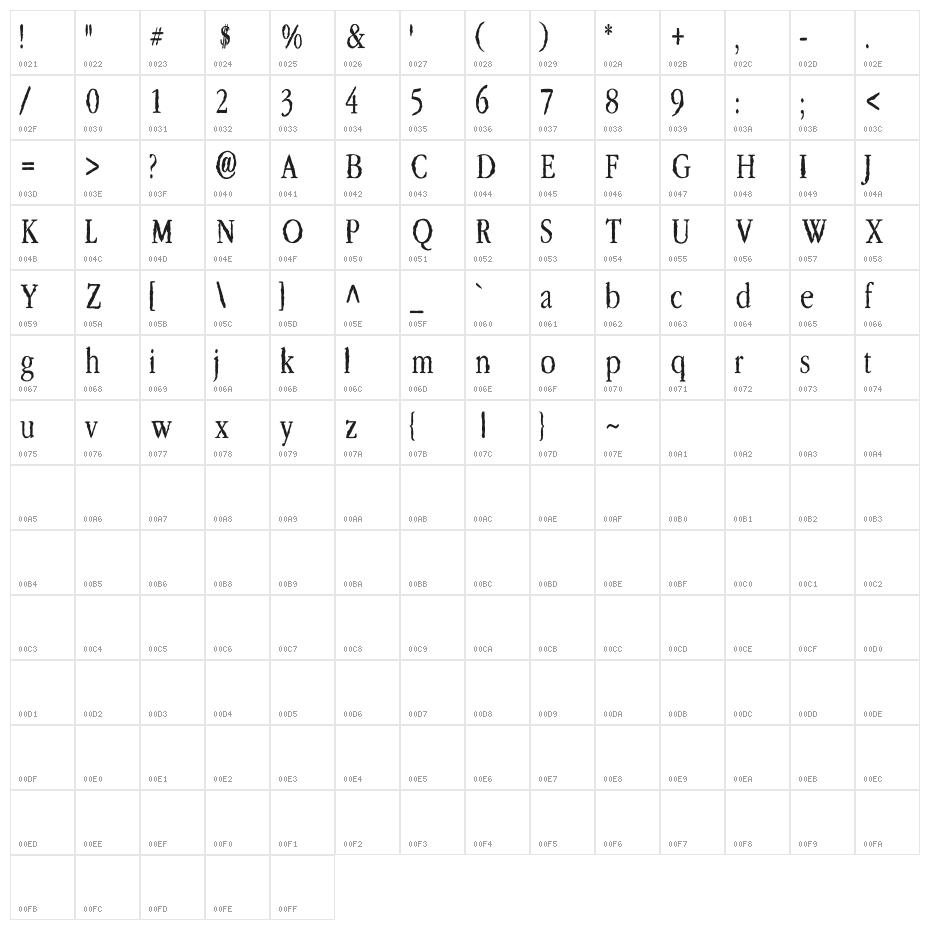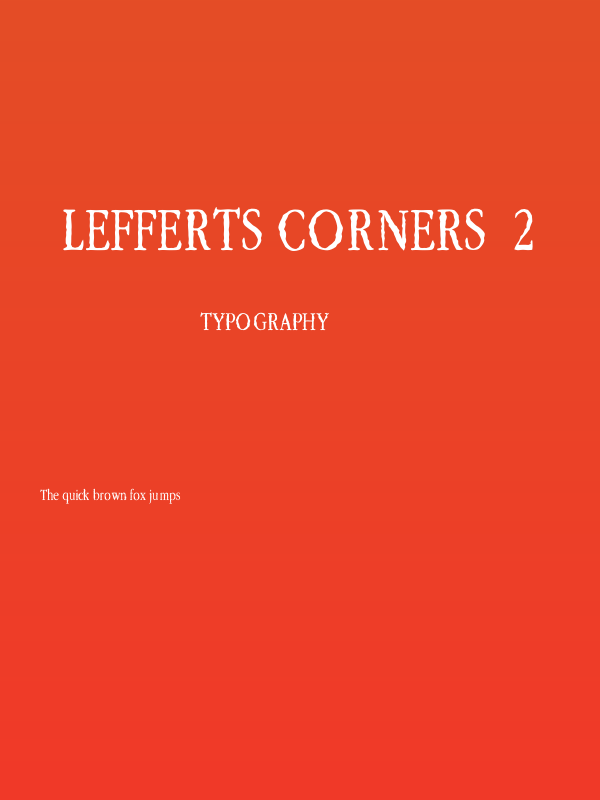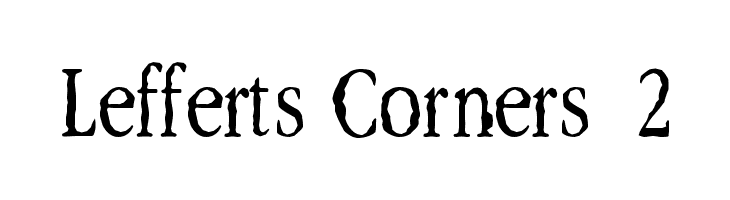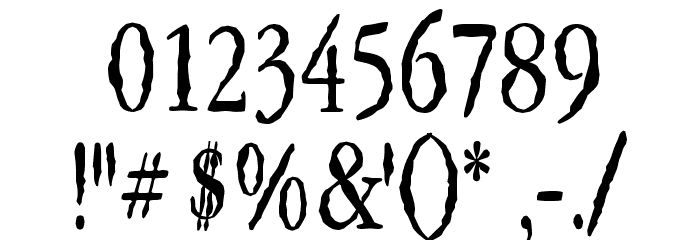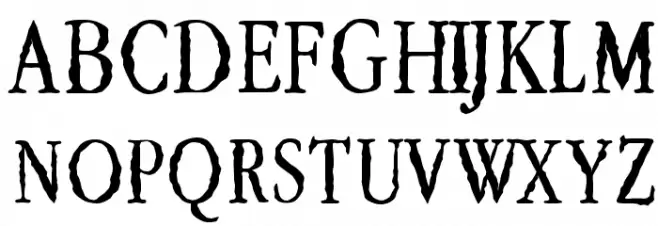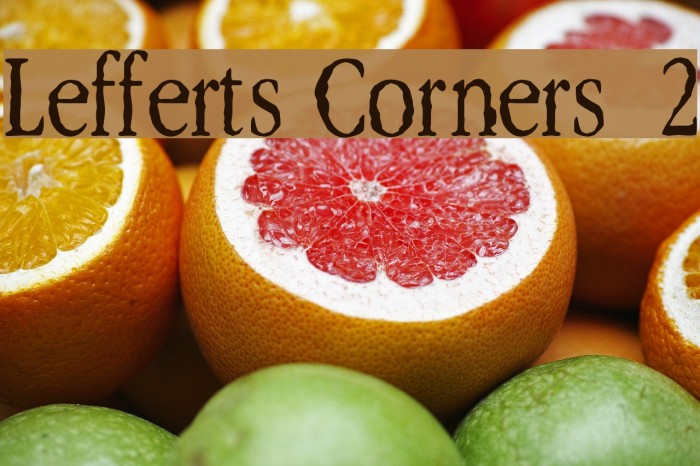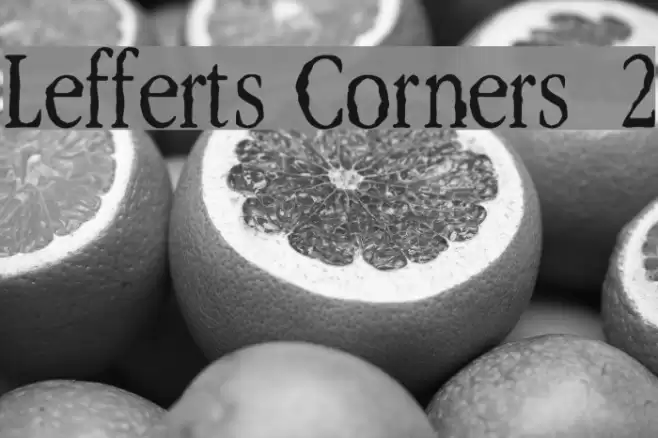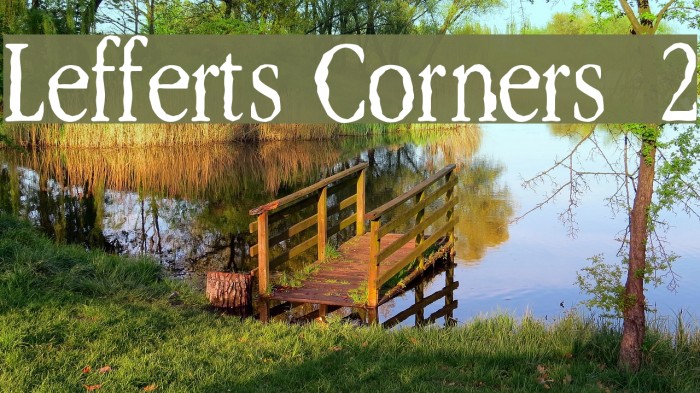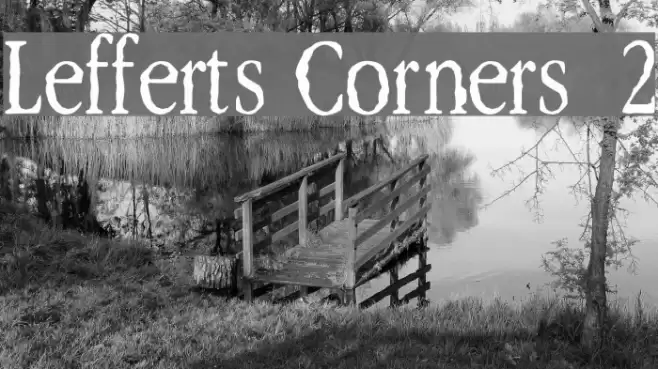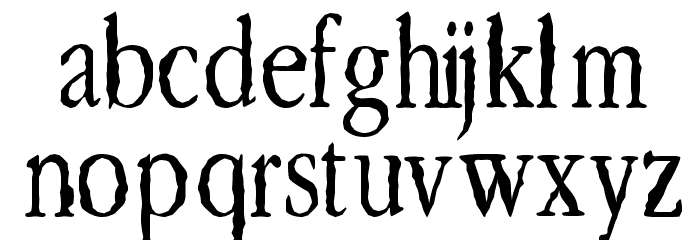
Lefferts Corners 2 Font
| Kategorien | Formal |
| Gesamtstil | Rustic |
| Anwendungsfall | Logos, Headlines, Invitations |
| Vorgeschlagene Projekte | Ideal for projects that require a personal, handcrafted feel, such as invitations, greeting cards, or artisanal product packaging. |